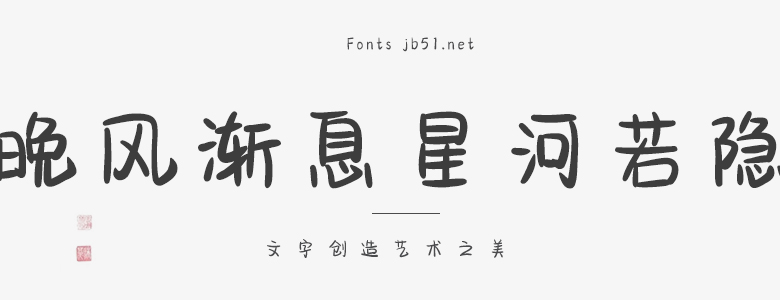
晚風(fēng)漸息星河若隱是一款獨(dú)特的字體,其設(shè)計(jì)靈感來(lái)源于大自然的美妙景觀。在夜晚,我們常常能夠感受到晚風(fēng)的輕柔與寧?kù)o,看到星河在夜空中若隱若現(xiàn)。這款字體將這兩種自然元素完美融合,以表現(xiàn)出一種優(yōu)美而神秘的氣息。 晚風(fēng)漸息星河若隱的字體設(shè)計(jì)細(xì)節(jié)豐富,特點(diǎn)鮮明。其筆畫(huà)流暢,線條優(yōu)美,字形舒展,給人以寬廣、舒適的感覺(jué)。每個(gè)字母的構(gòu)造都注重比例和平衡,以確保在不同的文本環(huán)境中都能夠呈現(xiàn)出最佳的視覺(jué)效果。 這款字體的應(yīng)用場(chǎng)景也非常廣泛。它適合用于一些寧?kù)o、優(yōu)雅的主題,如夜景、星空、自然景觀等。此外,它也適合用于一些需要呈現(xiàn)出優(yōu)雅、高貴氛圍的主題,如文學(xué)、詩(shī)歌、藝術(shù)品等。 總的來(lái)說(shuō),晚風(fēng)漸息星河若隱是一款充滿詩(shī)意和美感的字體,它能夠?qū)⒆匀辉嘏c人文藝術(shù)完美結(jié)合,給人以獨(dú)特的視覺(jué)享受。無(wú)論是在閱讀還是在設(shè)計(jì)中,它都是一款值得推薦的優(yōu)秀字體。